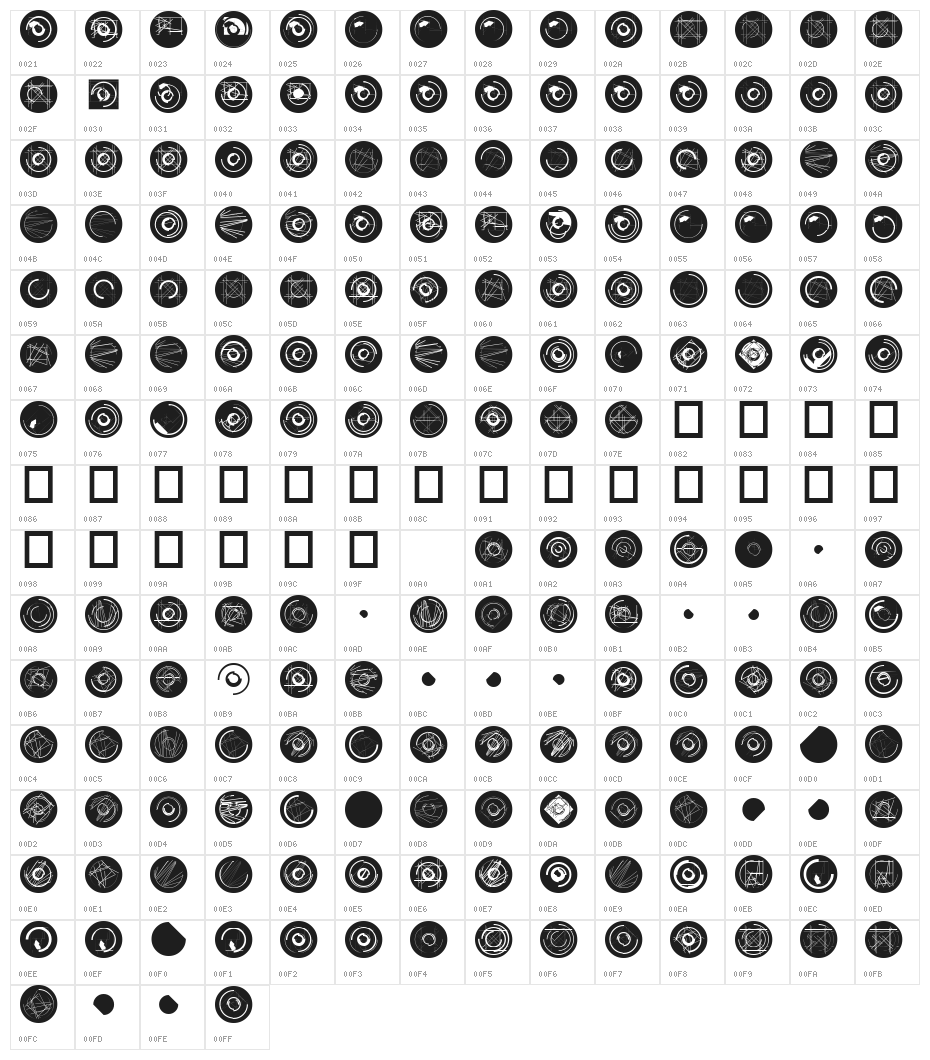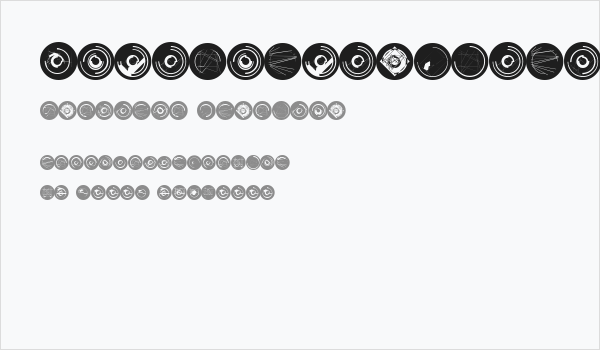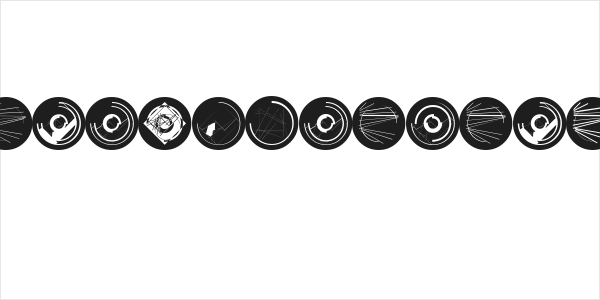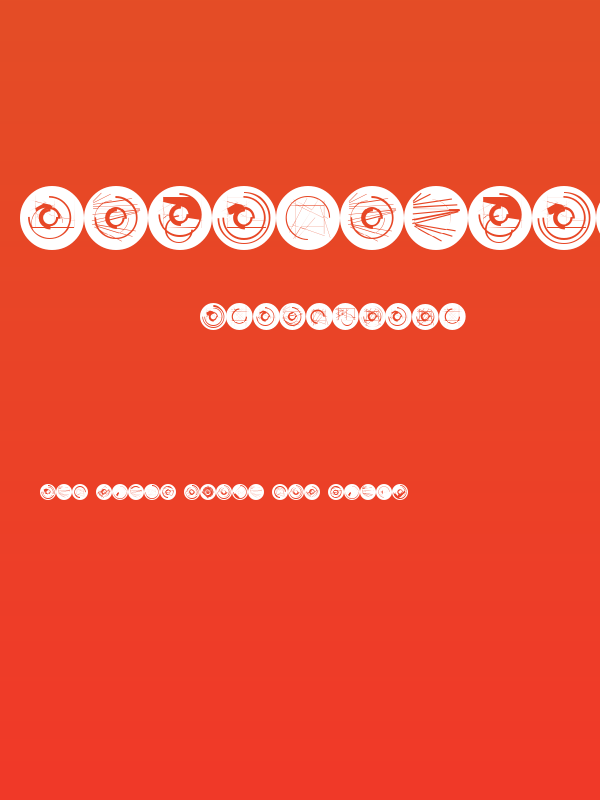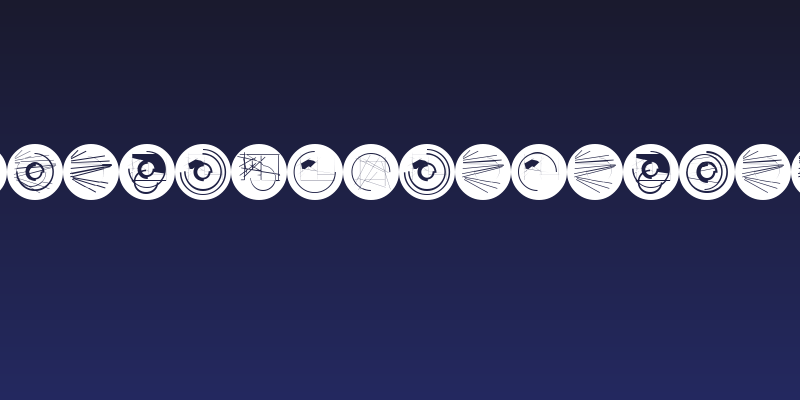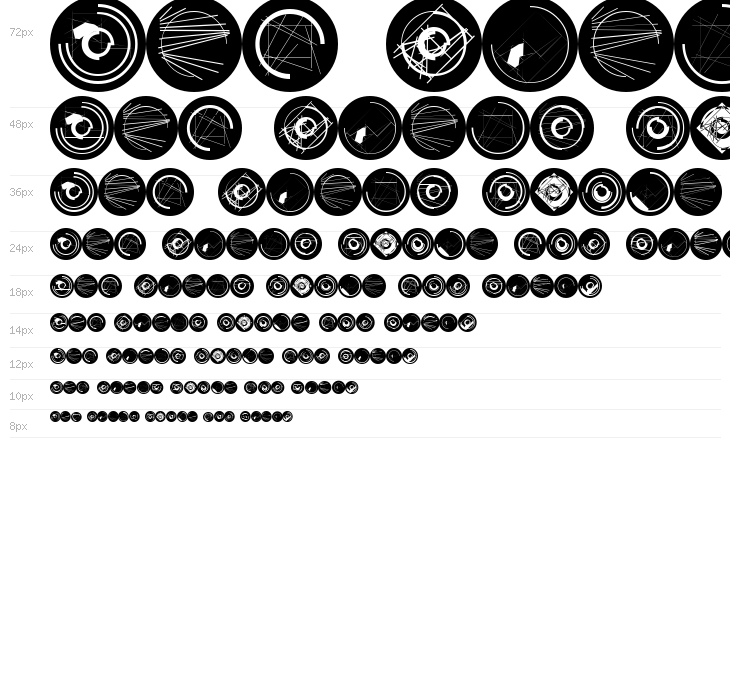
PostConstructivismInvers Font
| Categorie | Modern |
| Stile generale | Modern, Avant-garde |
| Caso d'uso | Logos, Art projects, Album covers |
| Progetti proposti | Ideal for artistic projects, modern art installations, album covers, or any design requiring a bold, abstract statement. |